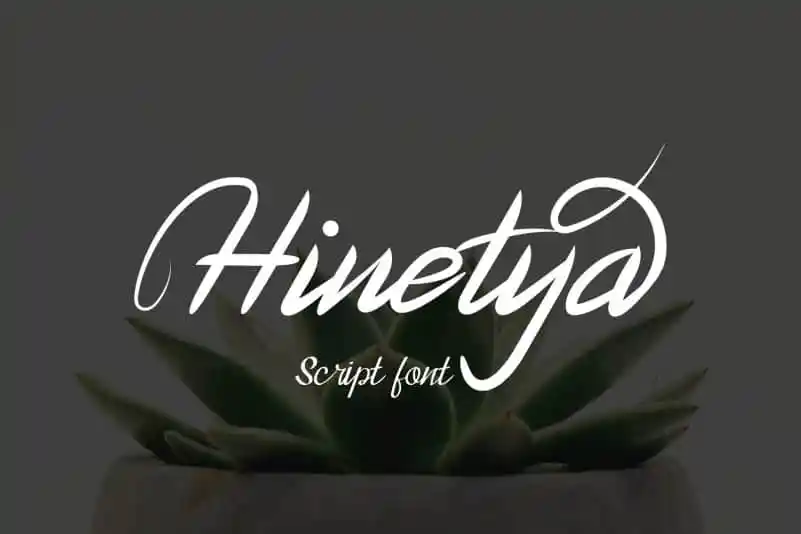
Hinetya Handwritten Font – Download Grátis
A Hinetya Handwritten Font é uma deliciosa e alegre fonte escrita à mão. Suas linhas leves e descontraídas tornam-a perfeita para um número impressionante de aplicações, incluindo logomarcas, identidades visuais, cartões de convite nupciais, arte de cartão de papel de parede belo, postagens impactantes nas redes sociais, e até mesmo cartões de saudação adoráveis. Esta fonte é perfeita para aqueles que buscam um toque natural e amigável em seus projetos visuais. Seja você um designer gráfico ou criador de conteúdo online, a Hinetya Handwritten Font certamente vai fazer seu trabalho!